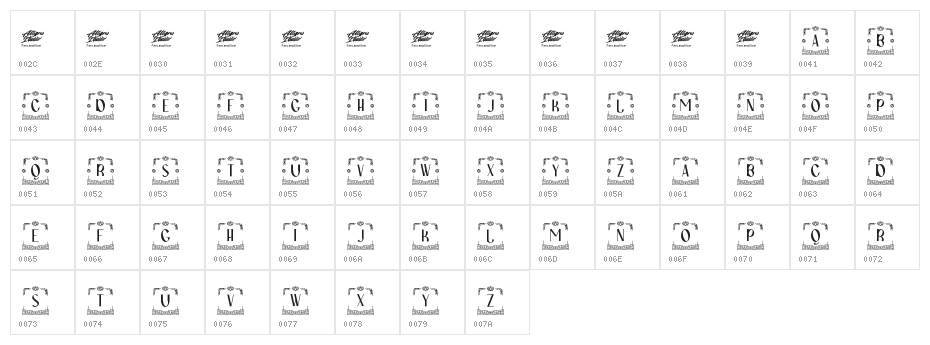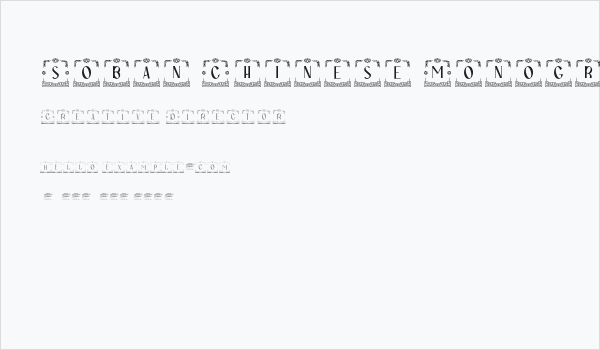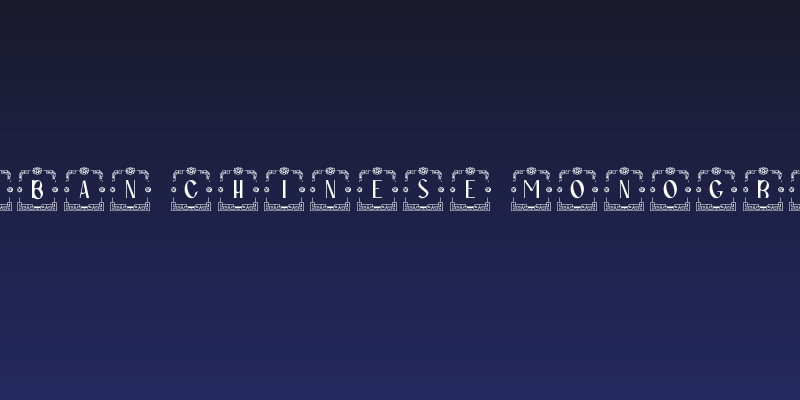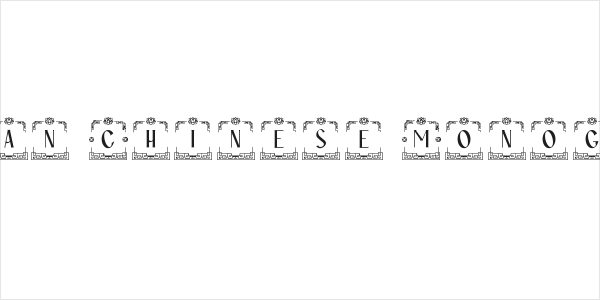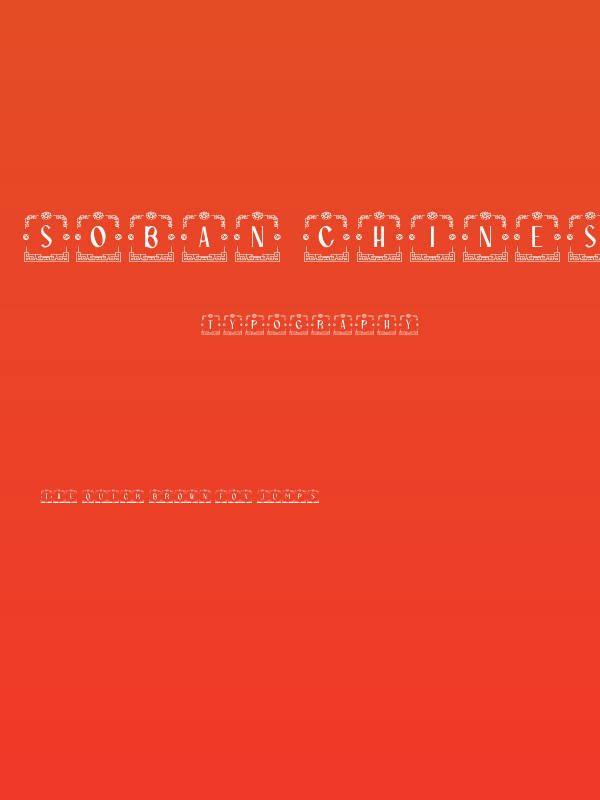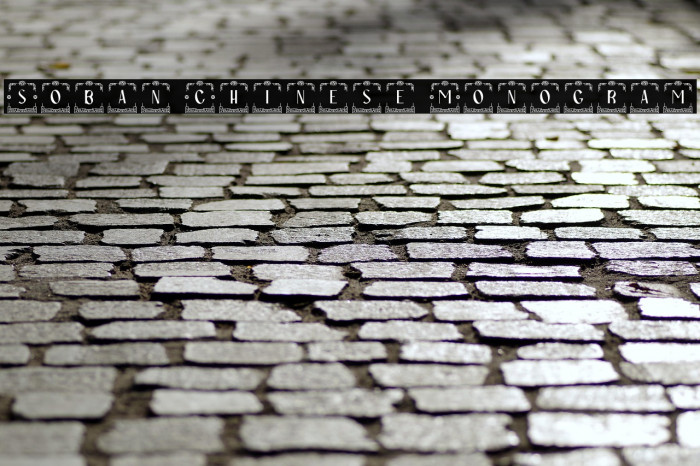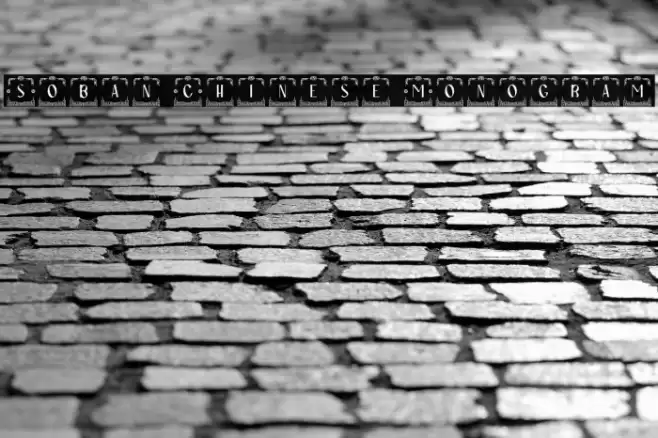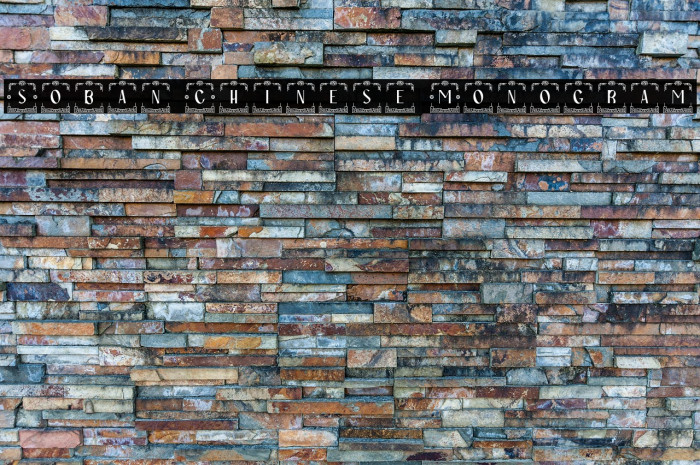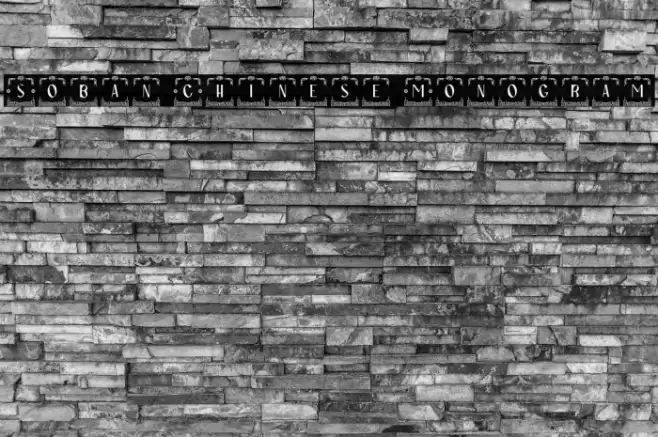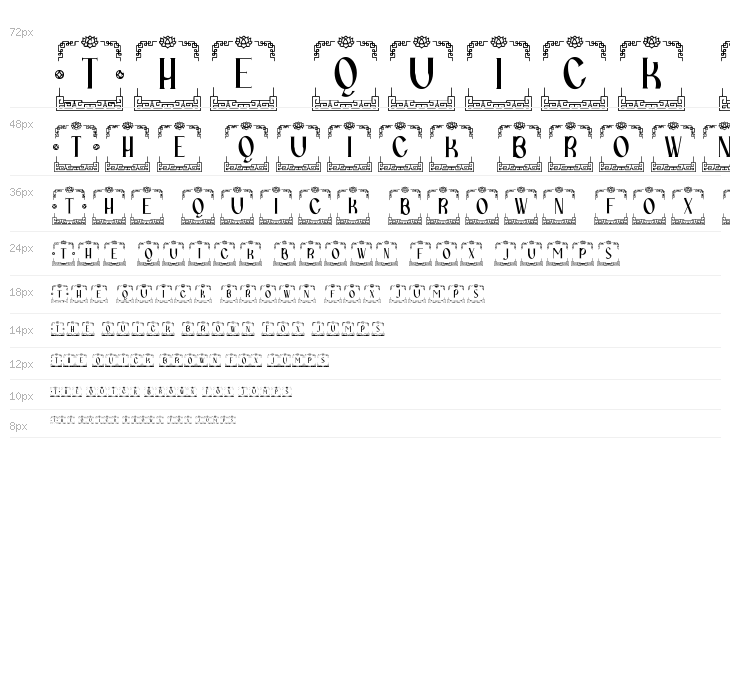
Soban Chinese Monogram Font
✎ Fancy
Fonts by Attype Studio
| 分类 | Fancy |
| 使用场景 | Logos, Invitations, Posters |
| 推荐项目 | Ideal for wedding invitations, cultural event posters, luxury branding, and decorative monograms. |
| 作者 | Fonts by Attype Studio |
| 分类 | Fancy |